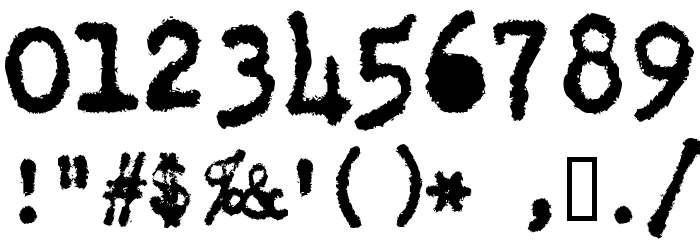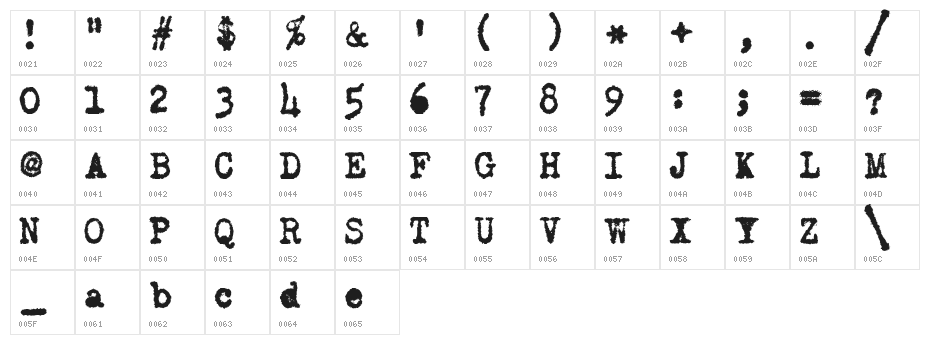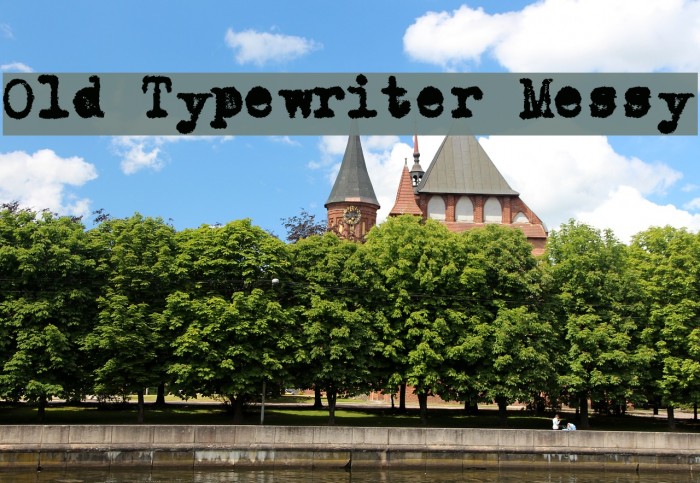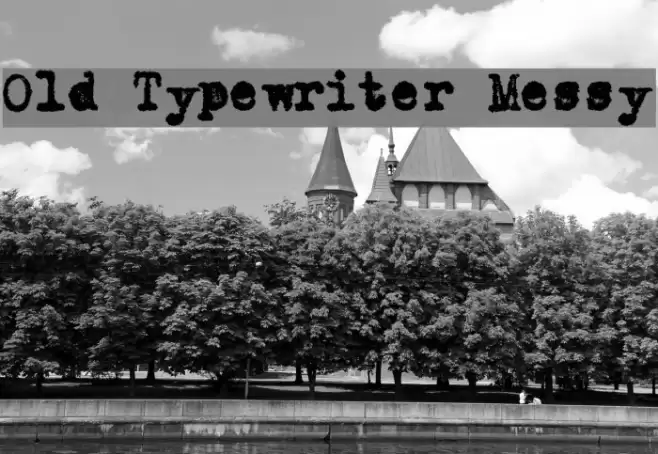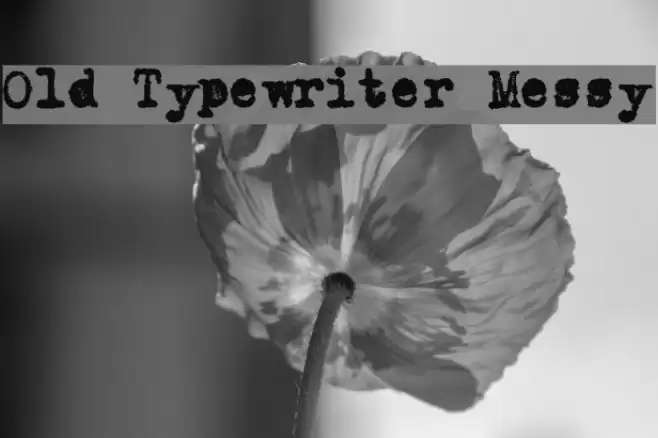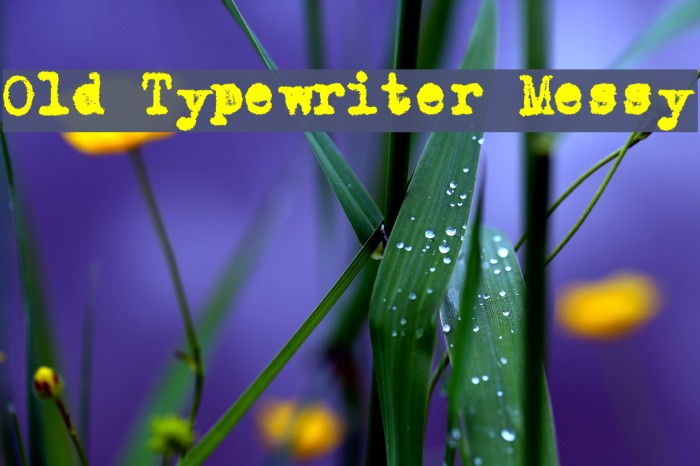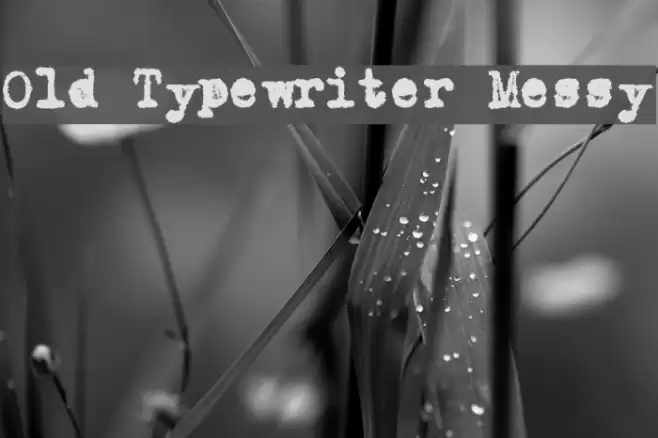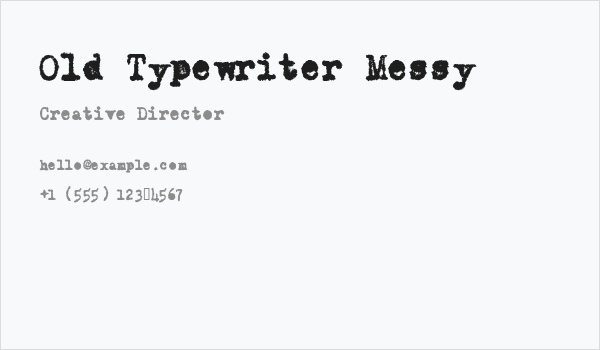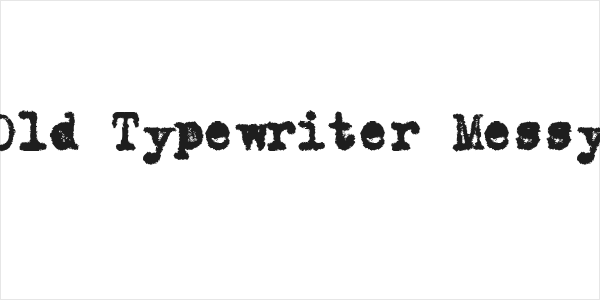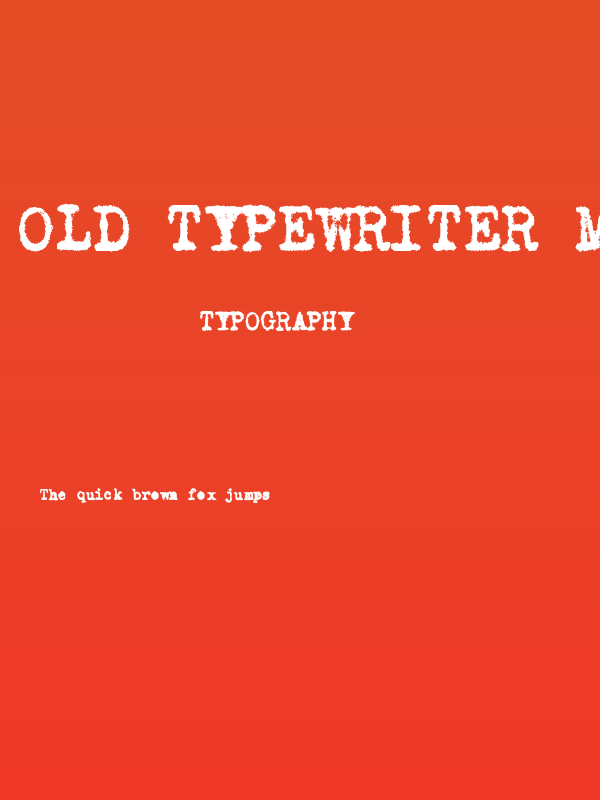
Old Typewriter Messy Font
| समग्र शैली | Vintage |
| उपयोग का मामला | Headlines, Logos, Posters |
| सुझाए गए प्रोजेक्ट | Ideal for vintage-themed designs, posters, book covers, and creative projects that require a retro or grunge aesthetic. |